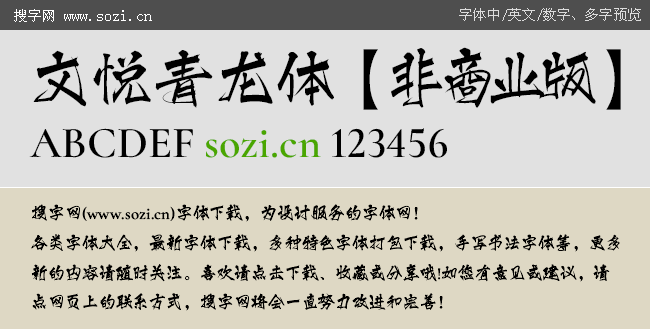
文悅青龍?bào)w【非商業(yè)版】
搜字網(wǎng)提供一款非常藝術(shù)的文悅青龍?bào)w【非商業(yè)版】下載,文悅青龍?bào)w是一款裝飾性極強(qiáng)的書法字體,以其飽滿的字面及獨(dú)特的蟹爪鉤為特色。一筆一劃鋒芒畢露,適用于包裝印刷、廣告設(shè)計(jì)、平面設(shè)計(jì)、海報(bào)設(shè)計(jì)等領(lǐng)域。